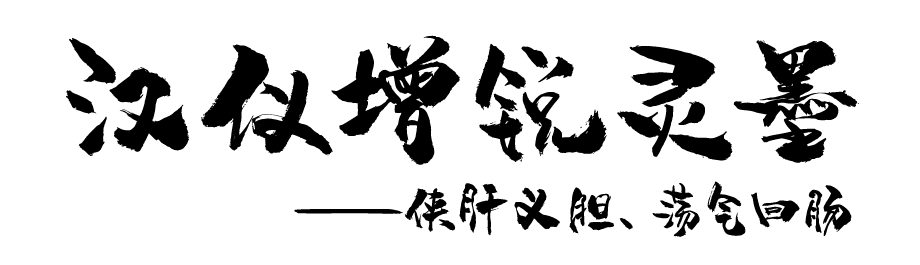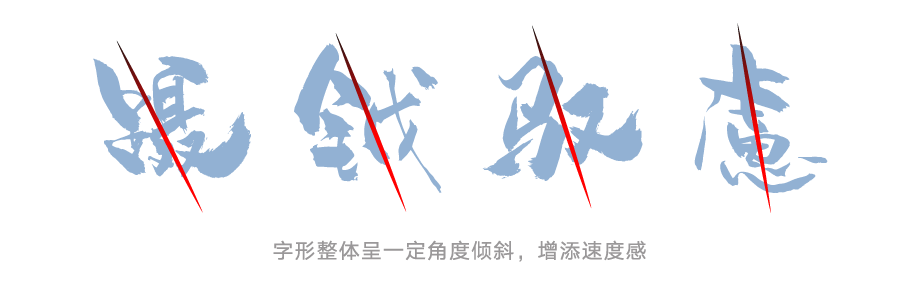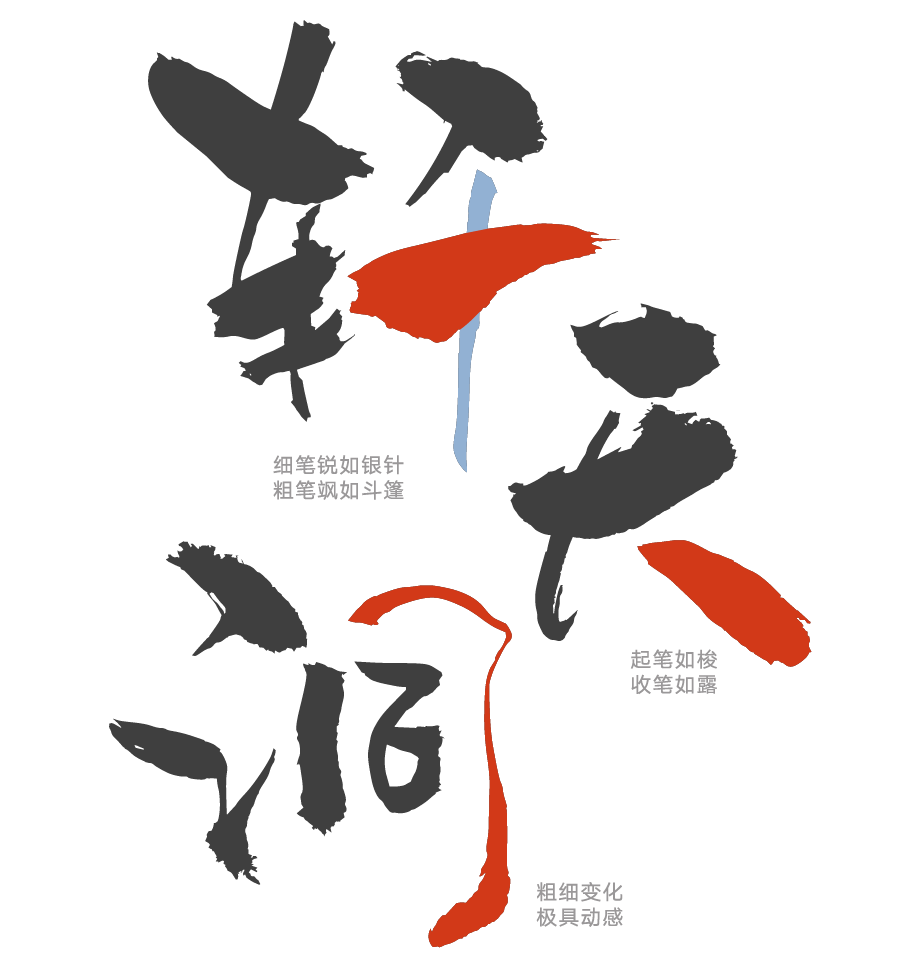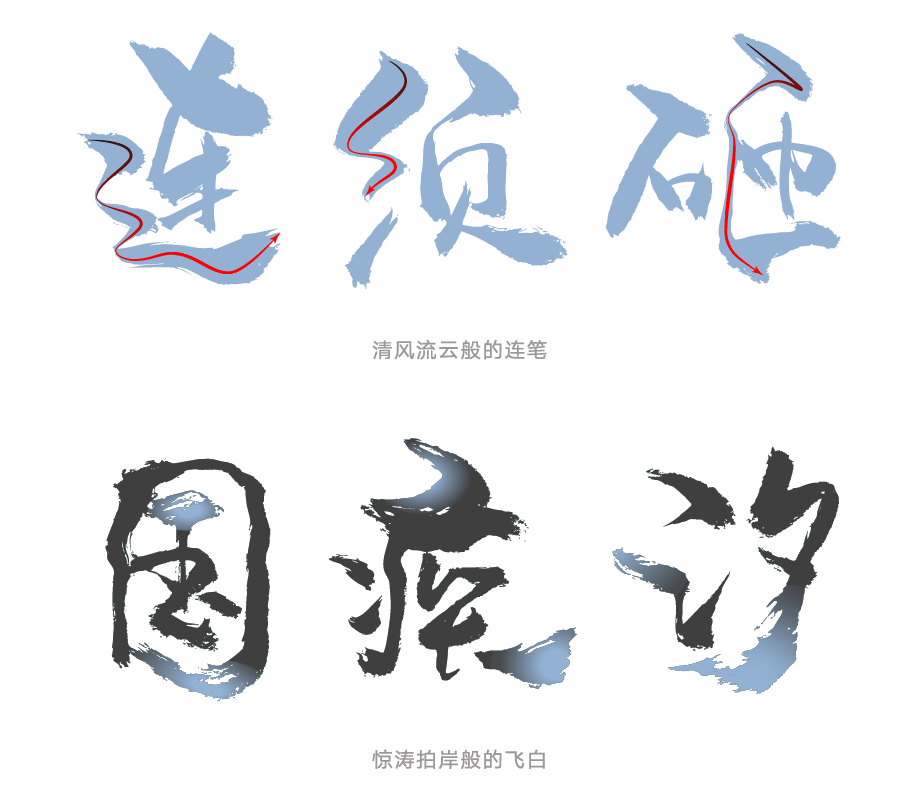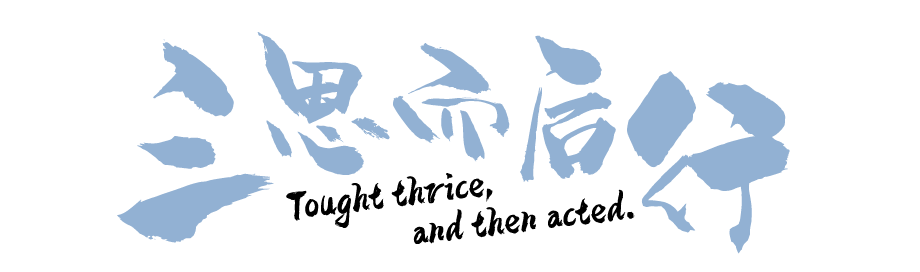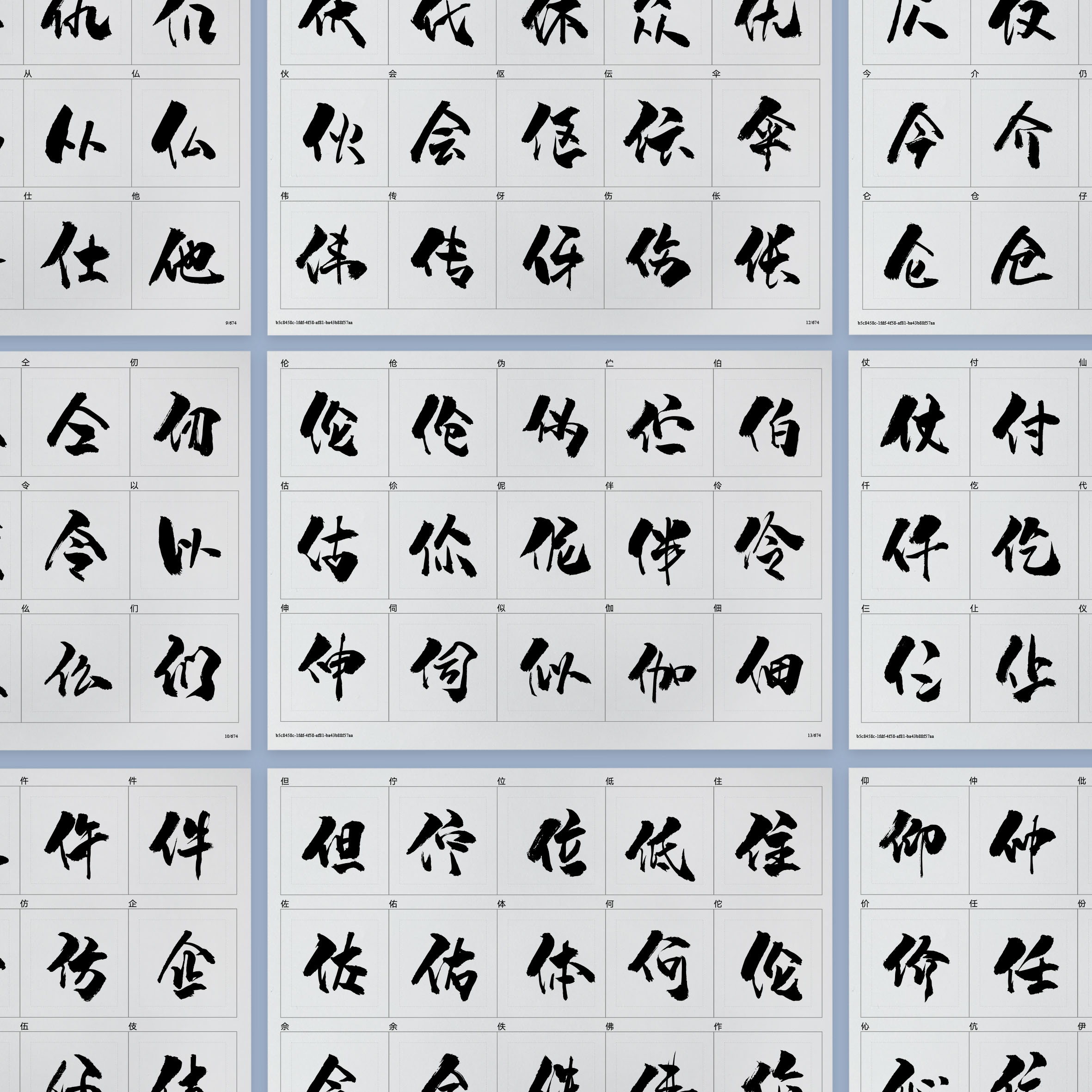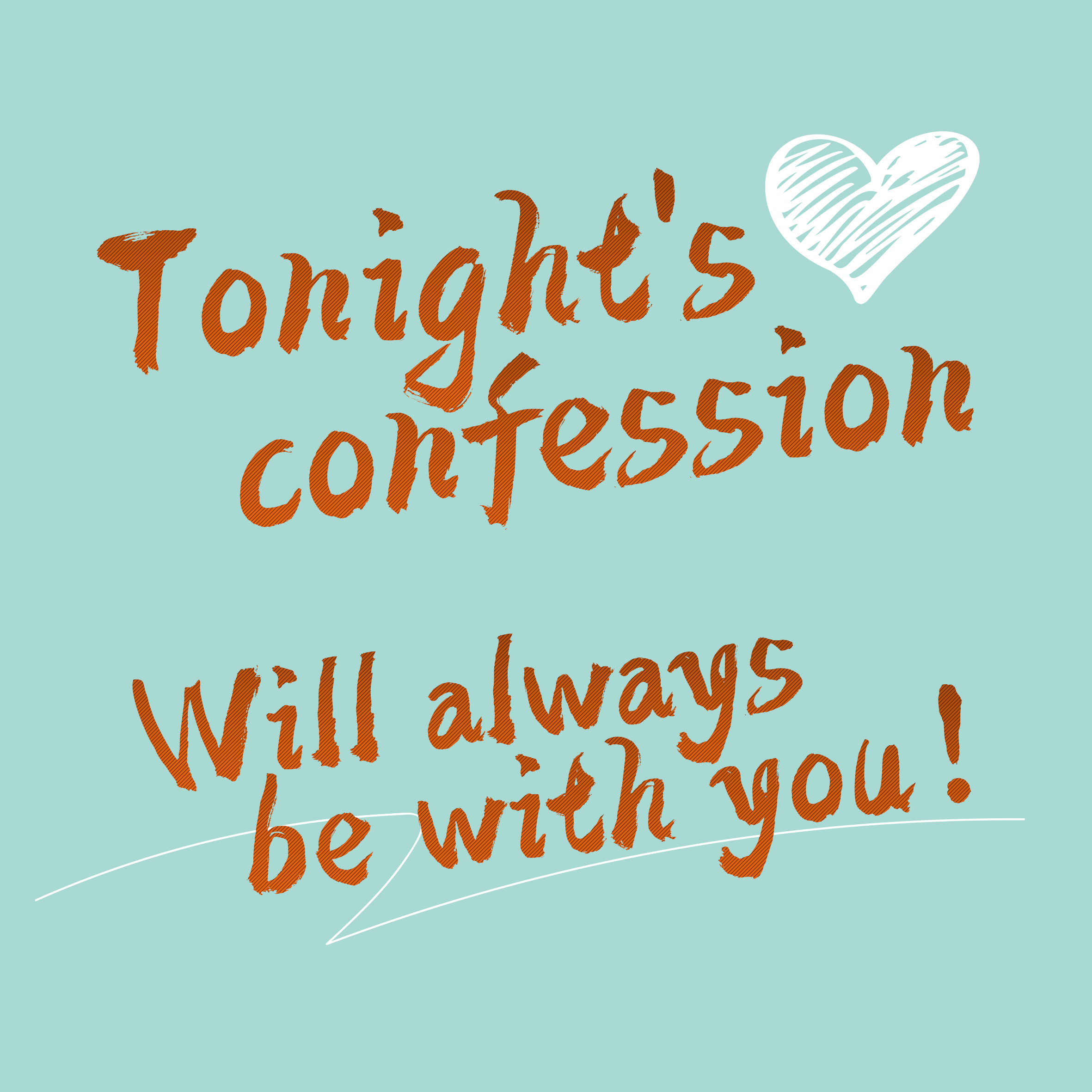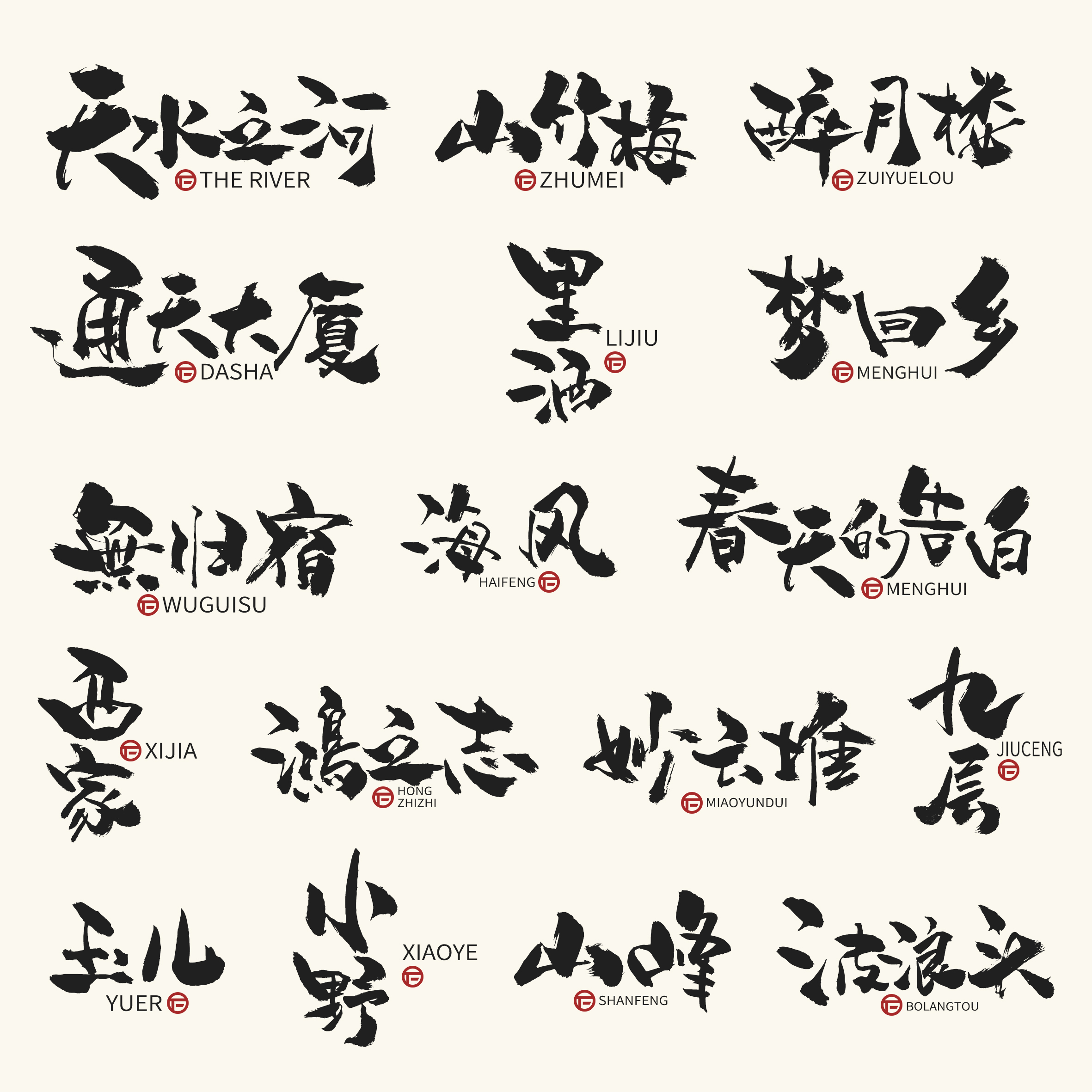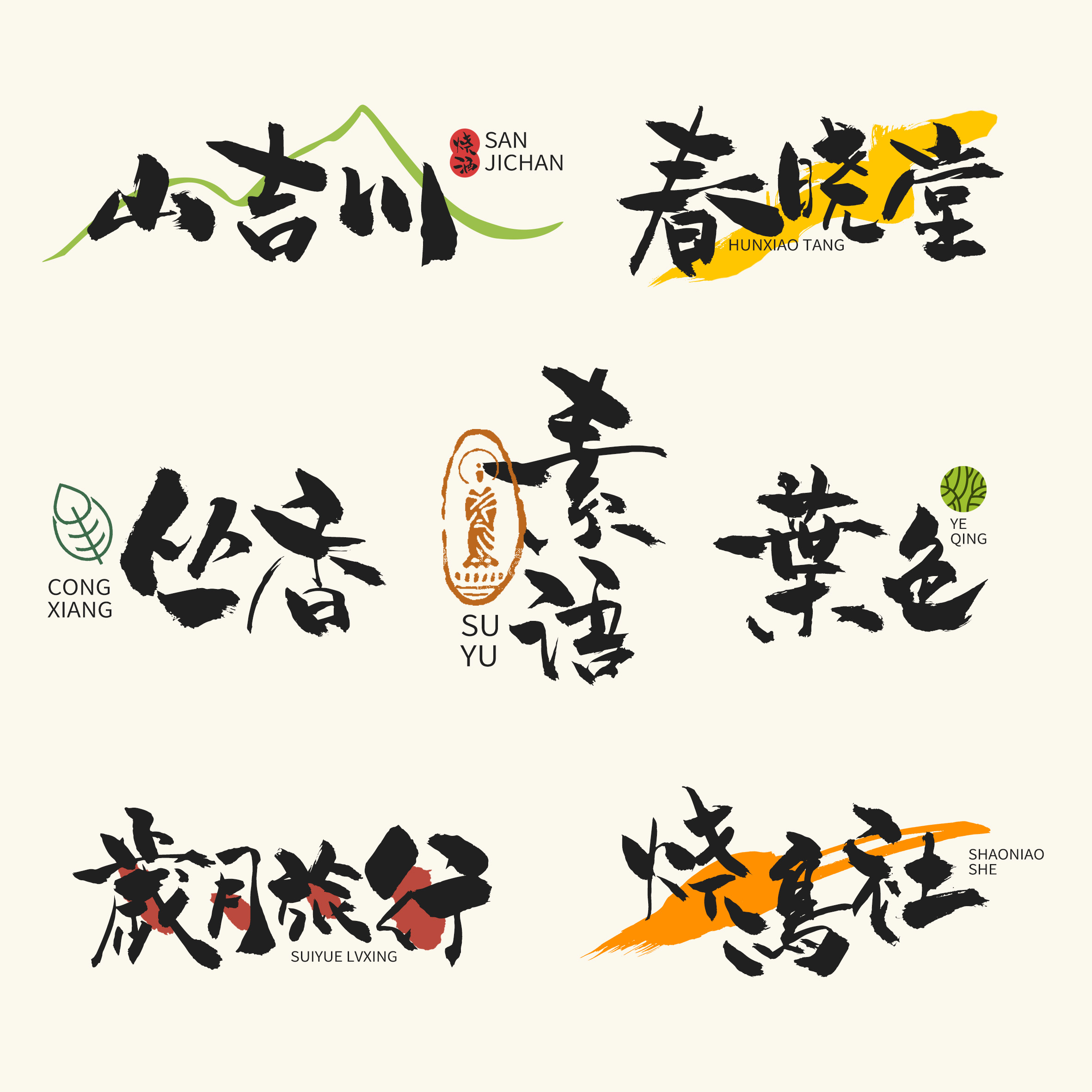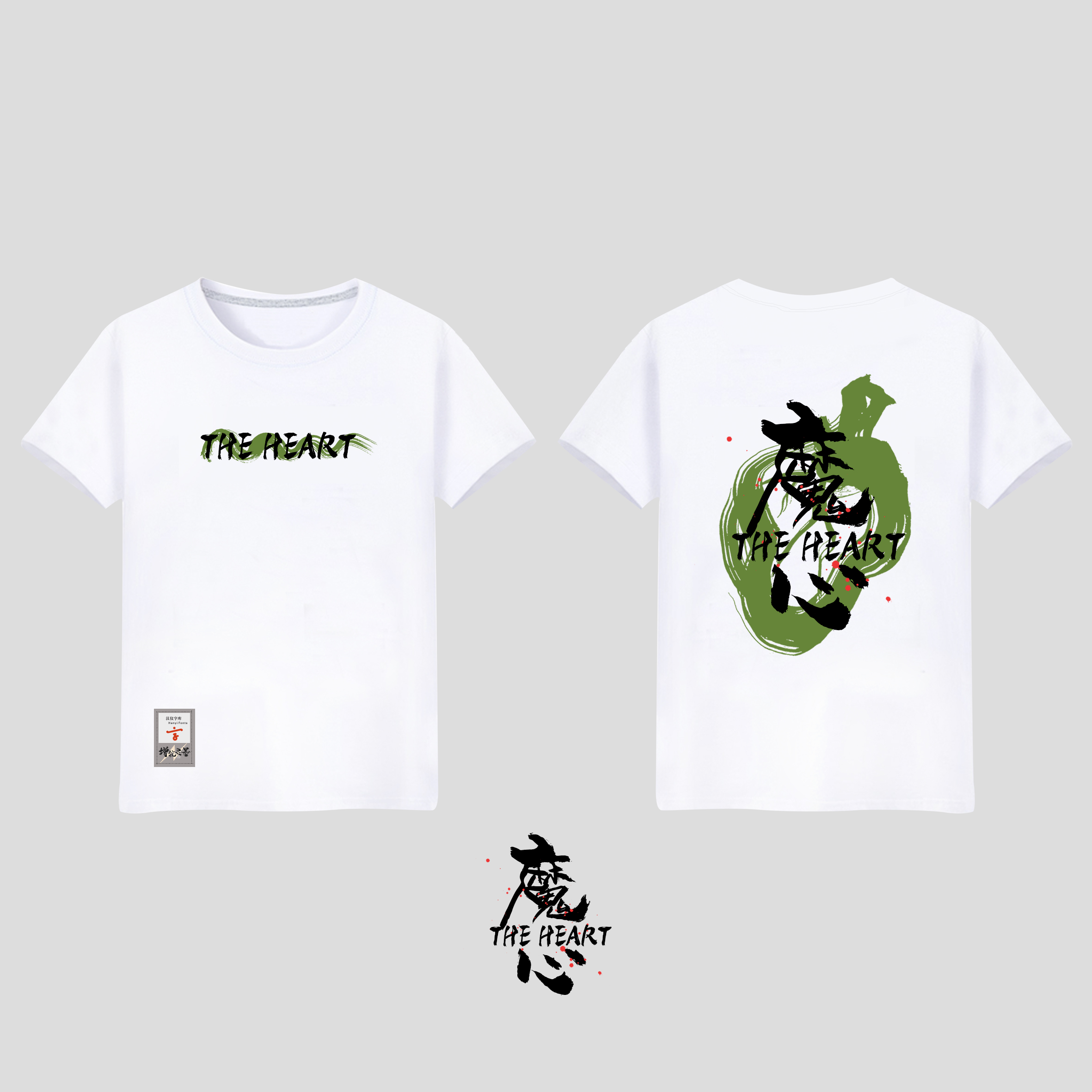
汉仪增锐灵墨字体介绍,一款侠肝义胆,荡气回肠的手写字
汉仪增锐灵墨 | 侠肝义胆、荡气回肠
汉仪增锐灵墨是由汉仪字库签约作者,放浪时光林增锐创作的一款极具动感、富有张力的手书字体。这款字体笔法灵动张扬,视觉冲击力极强,有着刀光剑影般的速度感与力量感。该字体适合用于游戏、影视、动漫等需要表现传统文化与速度力量相结合的场景。
汉仪增锐灵墨 | 结构紧实
汉仪增锐灵墨中宫紧实,重心略向左侧偏移,使得整个字体左收右放,富有张力。不同字形会根据字形特点做一定程度的向左倾斜,为字形增添速度感。
汉仪增锐灵墨 | 笔法灵动
汉仪增锐灵墨笔画粗细对比强烈。一字之内细笔锐如银针,粗笔飒如斗篷。起笔收笔或尖锐如梭、或充盈如露。部分笔画会有明显的粗细变化,如山间清流般或急或缓,极具动感。笔画主次分明,为字形增添强烈的视觉冲击力。
这款字体笔法灵动张扬,笔画错落,运笔流畅。笔法以枯笔为主,笔画间加入了大量连笔与飞白,使得字形更富烟云感,更具灵气。
汉仪增锐灵墨 | 中西文匹配
汉仪增锐灵墨的西文部分也是由作者书写。除了一些基础的拉丁字符,作者还绘制了部分西里尔字母、平假名、片假名和基本希腊字母。作者在西文的设计中也加入了大量飞白,为外文增添东方韵味。中西文混排风格一致,和谐自然。
汉仪增锐灵墨 | 草稿展示
汉仪增锐灵墨 | 排版展示
汉仪增锐灵墨 | 效果展示